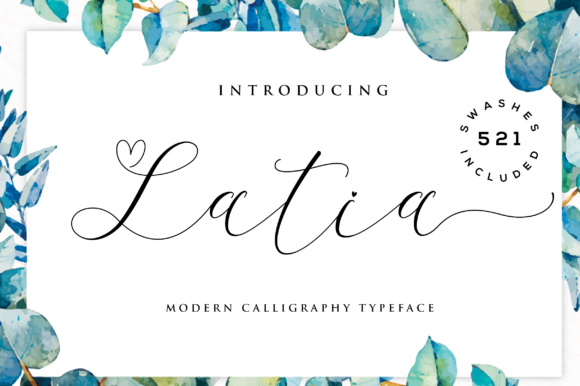
Latia Calligraphy Font
Escolha uma fonte de escrita aquarelada moderna é fácil de usar para qualquer design que você esteja criando. A Latia Calligraphy Font de Hamilton traz um toque pessoal, garantindo uma aparência elegante e moderna aos seus designs. Esta fonte tem uma maneira simples e refinada de escrever que cria um estilo de escrita aquarelada impressionante. Ideal para aqueles que desejam dar um toque único e sofisticado em suas obras criativas, sem dúvida esta é uma opção perfeita. Através da Latia Calligraphy Font, você pode criar designs que transbordam personalidade e elegância com a simplicidade de apenas escrever. Um verdadeiro atalho para um design impecável e profissional. Experimente hoje mesmo a fonte de escrita aquarelada moderna Latia Calligraphy.